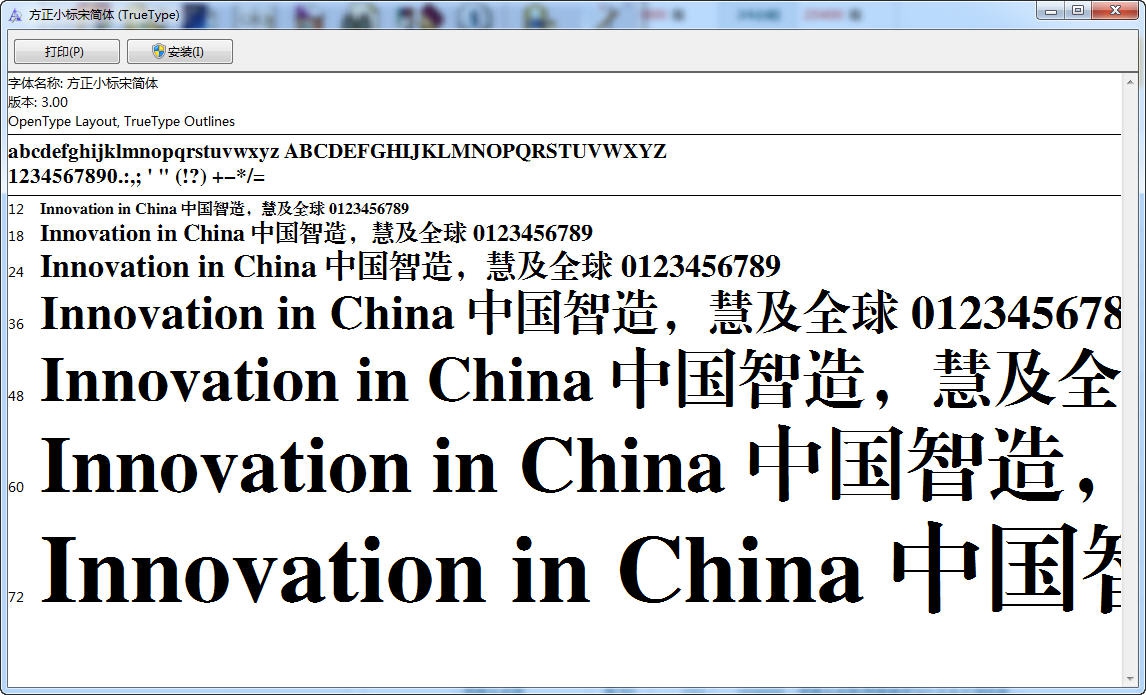
方正小标宋简体是广告的设计行业常用的字体,使用的范围十分的广泛,有着十分不错的粗体效果,是非常具有个人特色的字体软件,表现力也是非常强,感兴趣的用户快来绿色资源网下载吧!
按照《国家行政机关公文格式》(GB/T9704-1999)规定:行政机关公文的发文机关标识(即俗称的红头)推荐使用小标宋体字,用红色标识;公文标题应使用2号小标宋体字;公文主题词的词目应使用3号小标宋体字。而普通电脑一般未自带该字体,需手动下载安装。